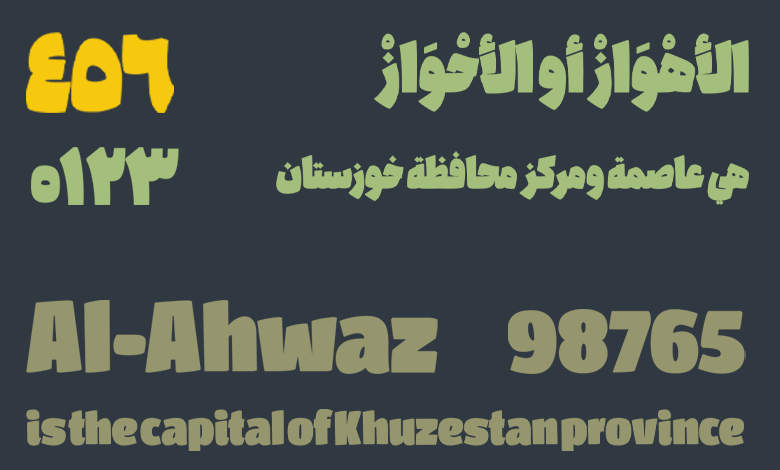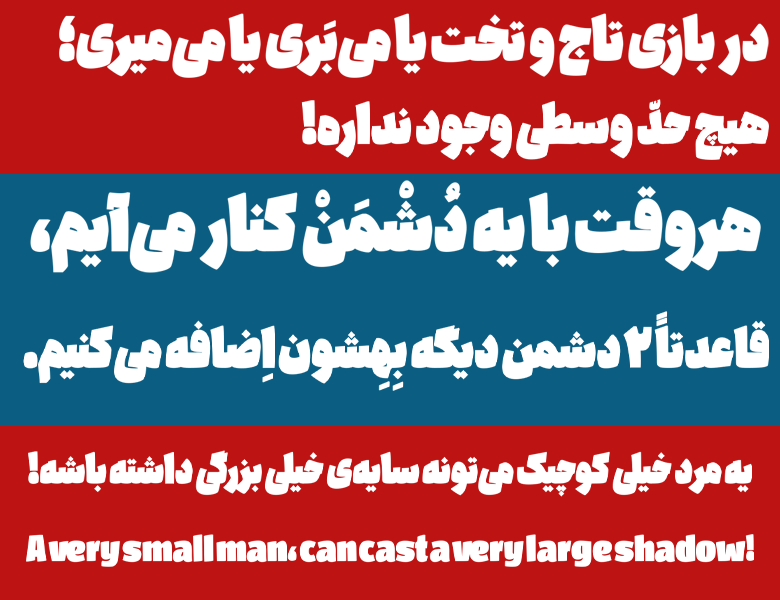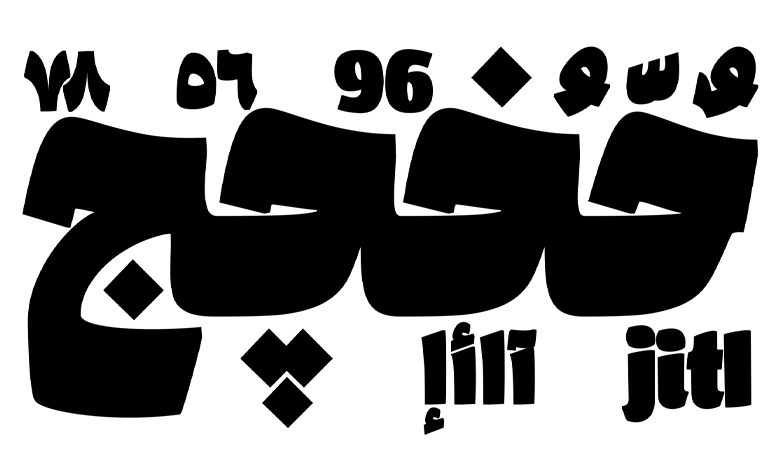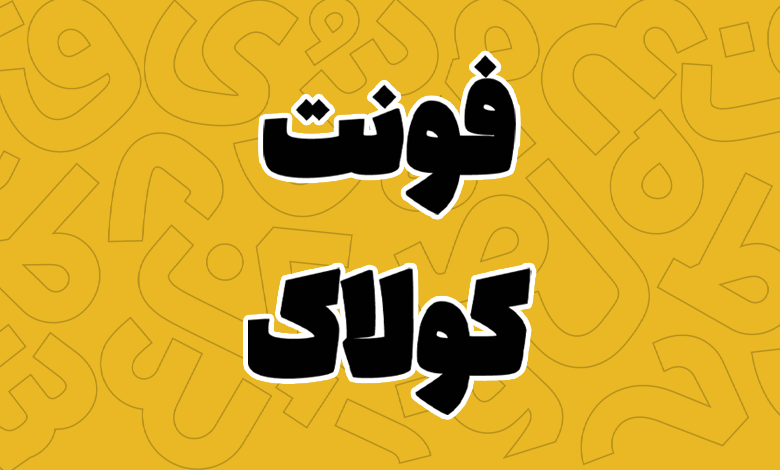
فونت کولاک (Colak)
فونت کولاک (به انگلیسی: Colak) از سری فونتهای پهن و مناسب عناوین، متنهای کوتاه، مطبوعات و تبلیغات است که در یک وزن با ساختار فوق سنگین و با سبک نسخ توسط امیر مصباحی طراحی گردیده است. این فونت شباهت نزدیکی به فونت لالهزار دارد و در همان سبک طراحی شده که به همین جهت میتوان آن را در گروه فونتهای نوستالژی نیز دستهبندی کرد. فونت کولاک رایگان نیست و با وزن Regular ساهته شده که در یک بسته اقتصادی قابل خریداری است.
این فونت اقتباسی از دیگر قلم این طراح فونت دماوند است که با هدف بهثمر نشستن ایده تایپفیسی سنگین با رویکردی رسمی و مدرن از آن فونت طراحی شده تا نیاز دو گروه از جامعه را برآورده سازد.
در ادامه این نوشته از سایت فونتچی به نقد و بررسی فونت کولاک خواهیم پرداخت؛ فونتی نوستالژی با وزن بسیار سنگین و پهن که از آن میتوان در عناوین و تبلیغات استفاده کرد. این فونت سرشار از خطوط هندسی، دارای طاهری نرم و دوستانه است که در ترکیب با یک فونت متن میتواند تاثیر فوقالعادهای روی خوانایی متون بلند داشته باشد.
ایده شکلگیری فونت کولاک، در یک روز سرد برفی شدید و کولاکی در شهر همدان شکل گرفته است؛ شهری در منطقهای کوهستانی که دارای زمستانهای سخت و سوزِ سرمایِ استخوانسوز است.
هنگامی که یک سیستم پرفشار با یک سیستم کم فشار برخورد میکند، کولاکها شکل میگیرند. به نوعی به اختلاف فشار بین دو سطح کولاک گفته میشود. به مقابله فضای سنگین مثبت با حداقل فضای منفی در یک سطح نیز گفته میشود.
امیر مصباحی؛ طراح فونت کولاک.
بنابراین ایده طراح برای ساخت این فونت، نیز بر اساس همین تعریف شکل گرفته است. ساختارهای مثبتی در فونت که در برابر بخشهای منفی قرار گرفته و نتیجه آن شکلگیری قلم کولاک شده است.
استایل و وزن فونت کولاک
طراحی فرم کاراکترهای کولاک متمایل به هندسه و از نرمی و سیالی متعادلتری نسبت به فونت دماوند است. طراح سعی کرده با حفظ روحیه رسمی، دوری از اغراق و همچنین محدود کردن فضای منفی در بین کاراکترها، فضای تایپوگرافی و گرافیک متفاوتری را به نمایش بگذارند.
همچنین فونت بر اساس پشتیبانی از زبانهای با اعداد فارسی به دو گروه تقسیم شده که فونتهایی با نامگذاری FD که مخفف FarsiDigits است، اعداد فارسی و عربی را به صورت هک شده در اختیارتان قرار خواهند داد که در ادامه بیشتر آنها را مورد بررسی قرار خواهیم داد.
پشتیبانی از ۶ زبان مختلف
فونت فارسی کولاک محدود به این فونت نبوده و با توجه به پشتیبانی کامل از ۶ زبان مختلف، تمرکز اصلی خود را روی پشتیبانی از زبان کردی و عربی دارد. دلیل تمرکز روی این زبانها نیز مملو بودن آنها به انواع اعراب و گلیفهای تزئینی است.
اگر به دنبال یک فونت عربی پهن هستید، کولاک میتواند در لیست فونتهای پهن در اولویت شما قرار گیرد. این فونت در نسخه زبانهای خاورمیانهای همچون عربی، کردی، اردو و ترکی که بر اساس قلم فارسی هستند، از تایپ اعداد فارسی پشتیبانی کرده و همچنین تفاوتهای جزئی همچون اعداد «۴۵۶» یا حروف «ک، ه، ی» که در زبان عربی وجود دارد را پشتیبانی میکند.
پشتیبانی این فونت کردی در این زبان نیز جزو زبانهای اصلی آن است. در زبان کردی هم شاهد استفاده از انواع گلیفهایی هستیم که یا جنبه تزئینی دارند و یا اینکه به عنوان اعراب استفاده میشوند. این زبان با توجه به نوشتار و ساختار متفاوتی که در خوانایی دارد، نیازمند یک استاندارد خاصتری نصبت به سایر زبانهای مبتنی بر حروف فارسی است که در این فونت به صورت کامل روی آن کار شده است.
در فونت انگلیسی کولاک نیز همان طراحی ضخیم پیادهسازی شده تا هماهنگ با زبان فارسی بوده و لزومی به تغییر قلم نداشته باشید. در زبان انگلیسی هم چه حروف لاتین و چه اعداد و کاراکترهای خاص دیگر، همان ساختار وزن سنگین را پشتیبانی میکنند.
تنها ایرادی که فعلا میتوان به این فونت گرفت در نسخه لاتین است که کلمات بههم نزدیک هستند و انتظار میرود این فاصله کلمات در آپدیت بعدی کمی بیشتر شده و بهبود یابد.
دارای گلیف های متنوع تزئینی و اعداد فارسی
دیگر ویژگی فونت colak پشتیبانی از گلیفهای خاص است. در این فونت فارسی که بر روی زبان کردی و عربی تمرکز ویژهای شده است، امکان استفاده از انواع اعراب مخصوص زبان عربی و همچنین گلیفهایی را خواهید داشت که در زبان کردی بسیار مورد استفاده قرار میگیرند.
اعداد در این فونت نیز از قابلیت هک اعداد فارسی و عربی پشتیبانی میکنند. یعنی بدون نیاز به تغییر زبان صفحه کلید به این زبانها، وقتی از فونتهای FD آن استفاده کنید، هنگام تایپ لاتین اعداد بهجای نمایش اعداد لاتین، فارسی نمایش داده خواهند شد. برای زبان عربی نیز اعداد «۴۵۶» با همان ساختار استاندارد تایپ خواهد شد.
با دانلود فونت کولاک برای فتوشاپ میتوانید از طریق تنظیمات Open Type به کلیه این گلیفهای تزئینی دسترسی داشته و از طریق فایل راهنمای Pdf موجود در بسته دانلود رایگان فونت کولاک، چگونگی استفاده از آنها را فرا بگیرید. این گلیفهای تزئینی برای تبلیغات و کارهای هنری و تاریخی میتوانند به بهتر کردن کار گرافیکی شما کمک کنند.
فونت نوستالژیک مناسب مطبوعات و عناوین
یکی از بهترین کاربردهایی که فونت کولاک رایگان دارد برای استفاده در مطبوعات است. در ساختار این فونت پهن شاهد یک پهنای نسبتا نزدیک به هم در تمامی بخشهای حروف هستیم که دارای زوایا و منحنیهای بسیار نرم و سیال است.